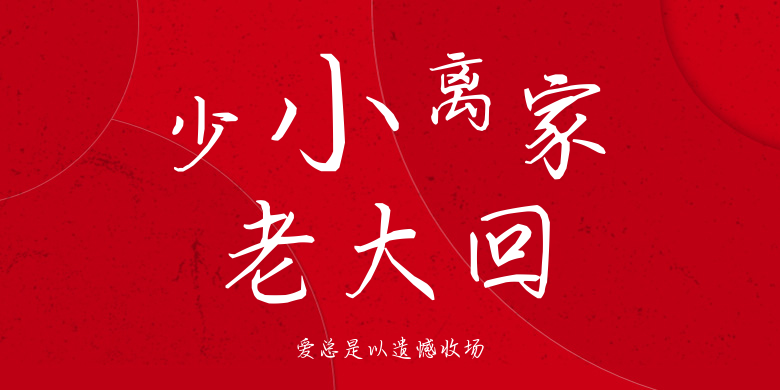
爱总是以遗憾收场
爱总是以遗憾收场,这款字体结构工整、笔画清晰,兼顾美观与易读性,适用于标题、正文、海报、包装、LOGO 等多种场景。字形优雅稳定,风格百搭耐看,适配日常排版与创意设计,让文字呈现更舒适、更具质感。爱总是以遗憾收场一笔一画,皆是细节,以均衡的比例、流畅的线条打造舒适视觉体验,字形端正大气,风格简约现代。无论是商业设计、品牌宣传还是日常排版,都能轻松驾驭,让文字更有格调与力量。爱总是以遗憾收场字体下载。